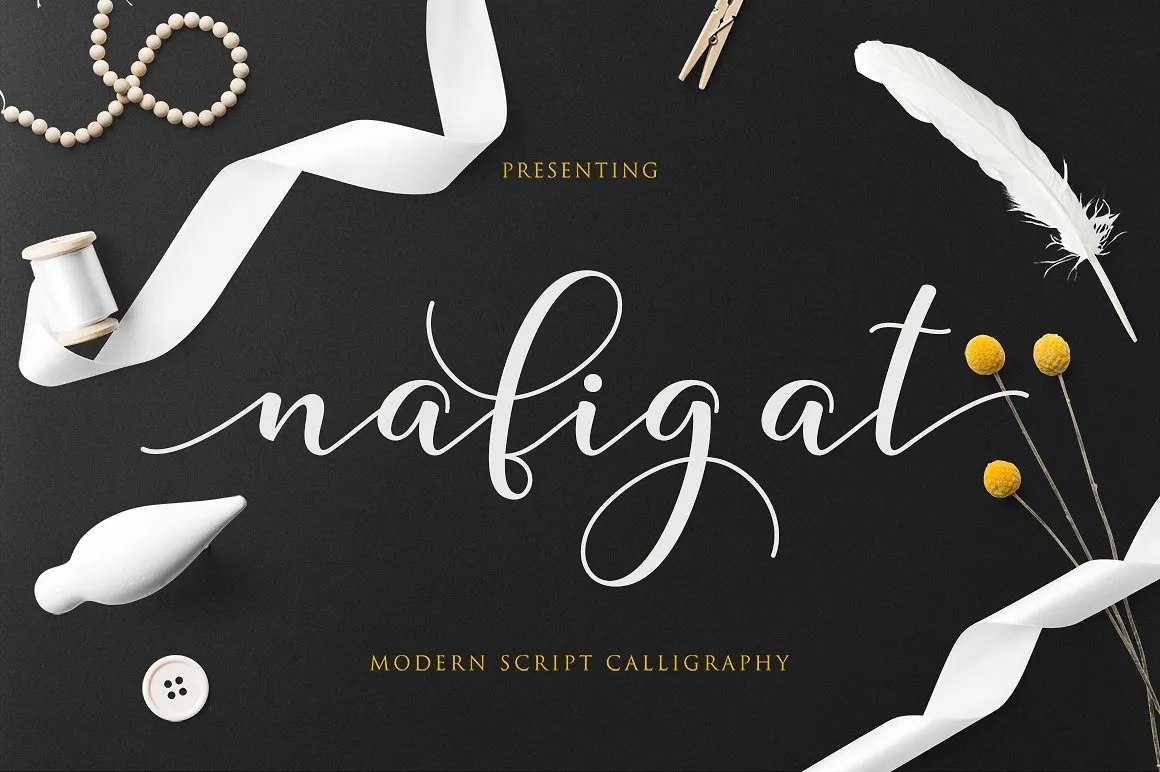
A Nafigat Script Font é uma elegante nova fonte script que combina elementos românticos com modernidade, criada por M.0Type. Esta fonte traz frescura e luxuosidade à sua próxima obra de arte gráfica, oferecendo 264 caracteres padrões e mais 408 alternativas em um formato de tipografia aberto. A Nafigat é perfeita para designers que desejam dar um toque único e inovador a seus projetos visuais, trazendo uma sensação única de romance moderno. Seja você criando cartões de visita personalizados ou projetando anúncios chamativos, a Nafigat Script Font estará sempre ao seu lado para oferecer o estilo fresco e luxuoso que você precisa.